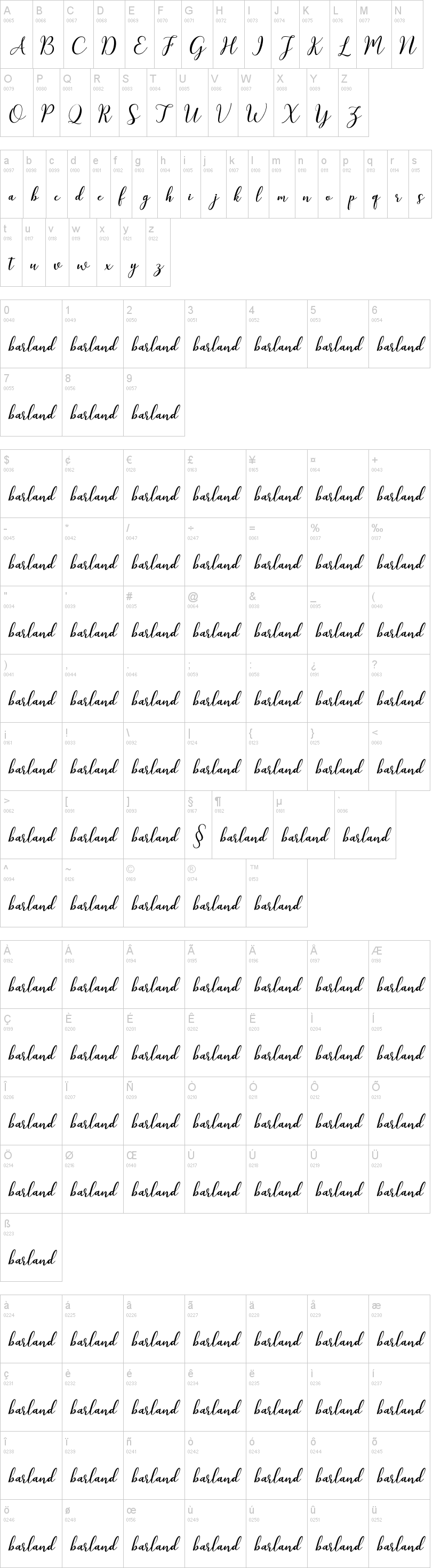
Kissita 是一款简洁优雅的英文字体,由著名设计师 Kissita 创作。它由圆润的曲线组成,具有明显的现代感,但又不失传统的美感,可以满足不同的设计需求。Kissita 字体可以应用于多种类型的设计,包括海报、广告、报纸、书籍、网站、社交媒体等。它的特点是清晰、大气、活泼,可以提升设计的质量和影响力。内容介绍
Kissita是一款非常不错的手写艺术字体,具有很好的视觉感,适合于文化类的宣传设计、商业类品牌的广告和产品包装设计以及个性化文字排版等较多场景。